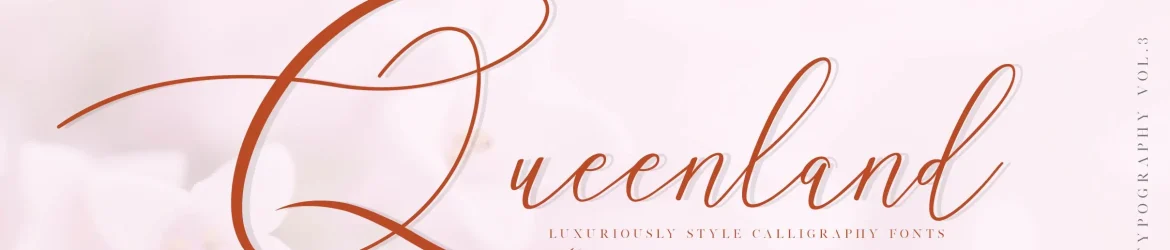
Queenland Script Font – Fonte Grátis
Queenland Script Font
A moderna fonte tipo “Queenland Script Font” oferece um toque elegante e sofisticado às suas criações de design. Introduzida por zziplex, esta fonte tipográfica escrita a mão é ideal para quem busca personalizar seus próximos projetos de arte com uma aparência autêntica. Com seu estilo único, Queenland oferece um look elegante e moderno que complementará desde logotipos e marcas até embalagens de produtos, assinaturas de eventos especiais e materiais fotográficos. Seja para personalizar etiquetas, adesivos ou mesmo mensagens no Instagram, a fonte “Queenland Script” tem o poder de transformar qualquer projeto com um toque autêntico e sofisticado.